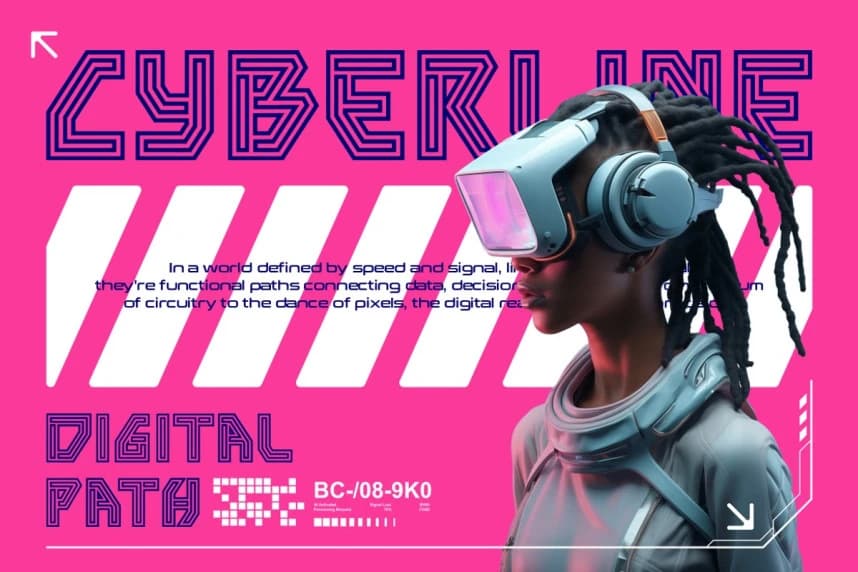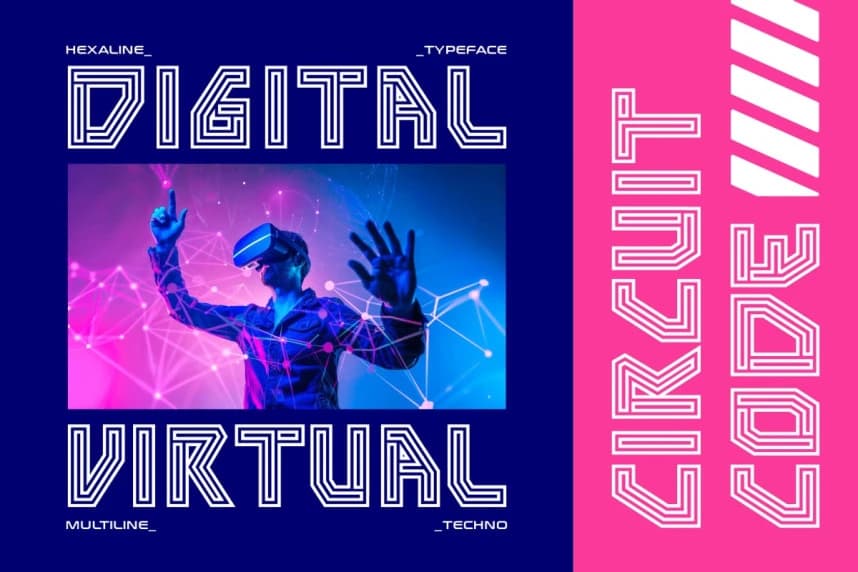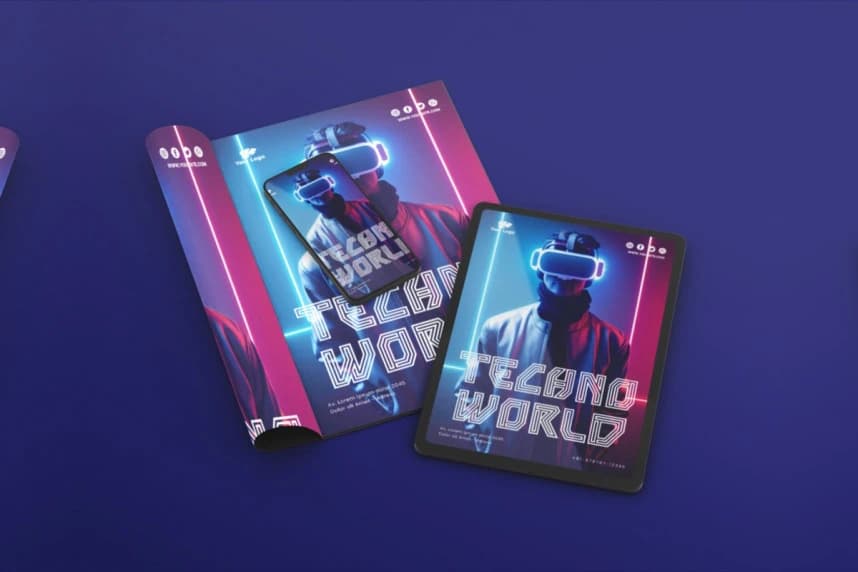
Hexaline Font
Hexaline Font - Multiline Tech Font, modern dijital bir keskinlik gerektiren projeler için tasarlanmış fütüristik bir yazı tipidir. Her harf formu temiz, geometrik hatlarla inşa edilmiştir ve çok satırlı bir etki yaratır; fonta belirgin bir devre temalı görünüm kazandırır.
Hexaline Font - Multiline Tech Font, modern dijital bir keskinlik isteyen projeler için tasarlanmış futuristik bir yazı tipidir. Her har biçimi temiz, geometrik hatlarla inşa edilmiştir ve çok satırlı bir etki yaratır, bu da fonta belirgin bir devre temalı görünüm kazandırır.